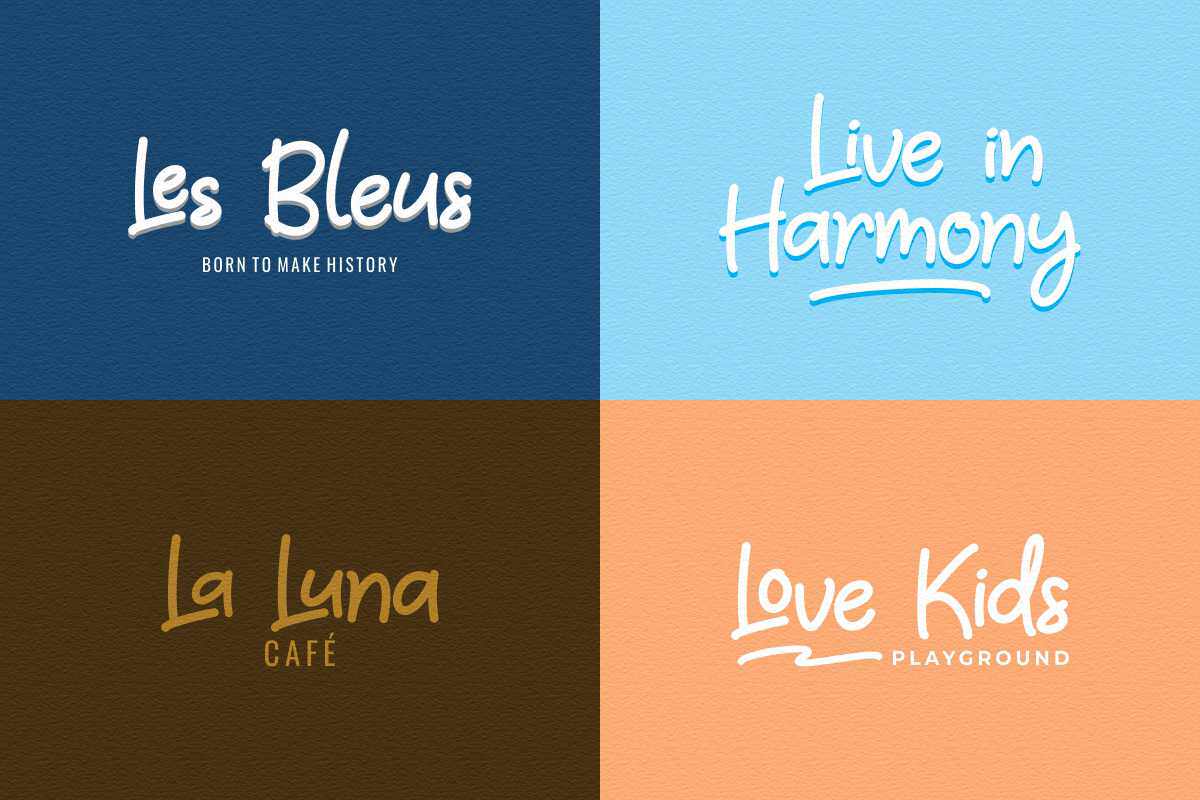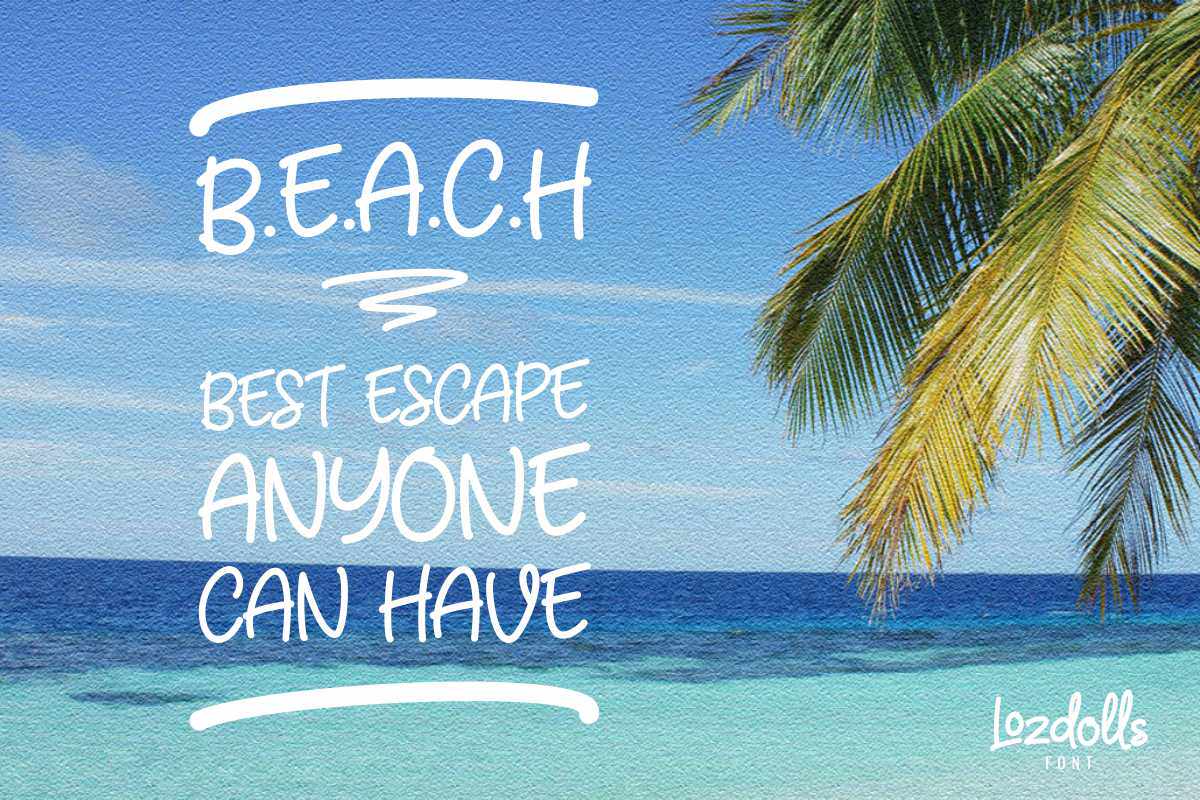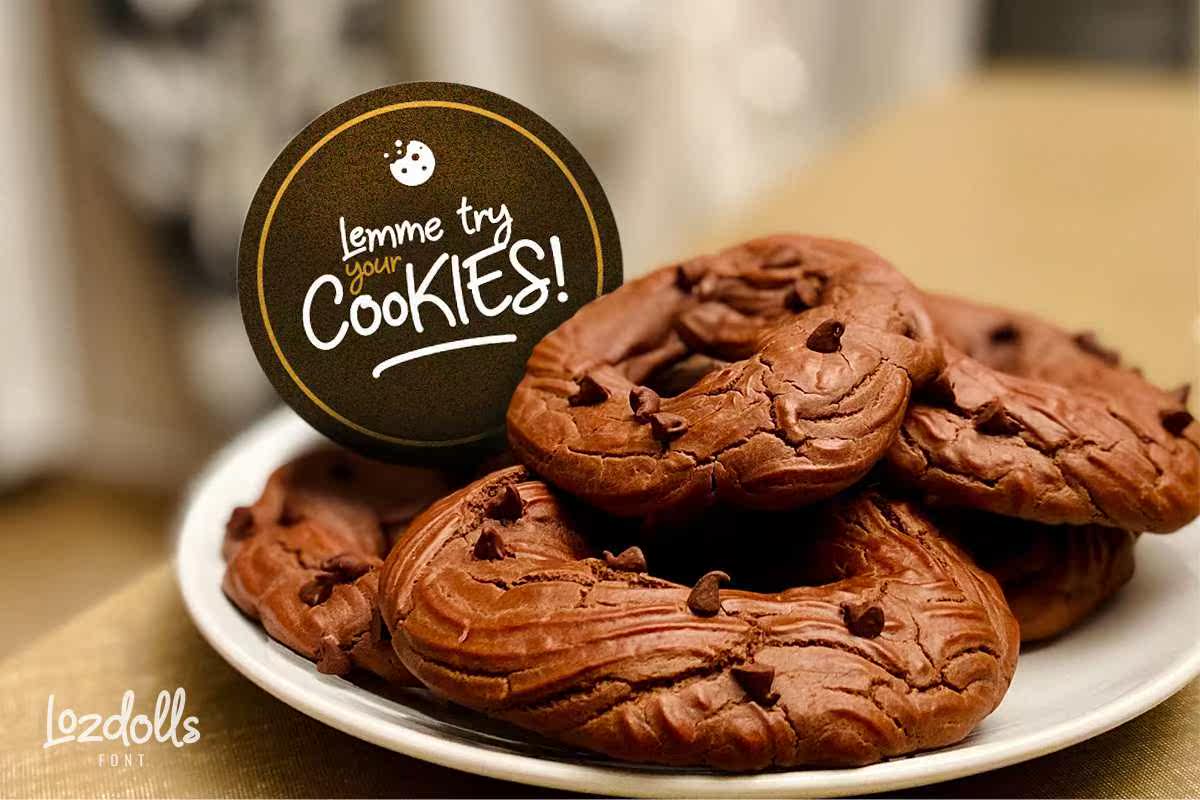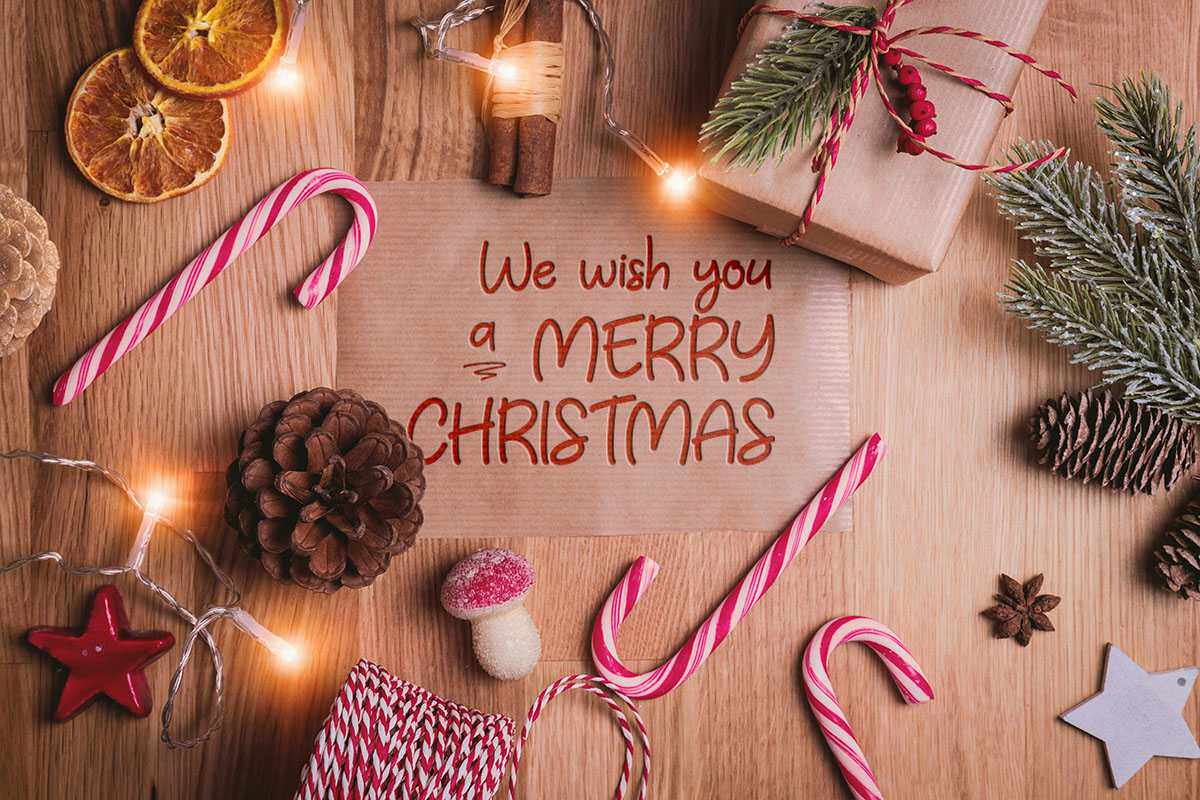
LozDollsisa和Written Font是一种用Amakerpen书写的字体,就像他们用Amakerpen书写的一样。这是一种认证和通用的字体,非常适合您的创意项目,如徽标和品牌、邀请函、传单、社交媒体设计、标签和包装等!这个字体看起来像是用小写字母书写的。它由连字、文体转换、涂鸦和多语言字符组成。lozdollsisa和writentfont都是用大写字母书写的,就像用Amakerpen书写的一样。这是一个认证和通用的字体,非常适合您的创意项目,如徽标和品牌、邀请、传单、社交媒体设计,标签包装等等!此字体在小写字母的大写字母中看起来很奇怪。它还包含连字、文体替换、换行符和多语言字符。